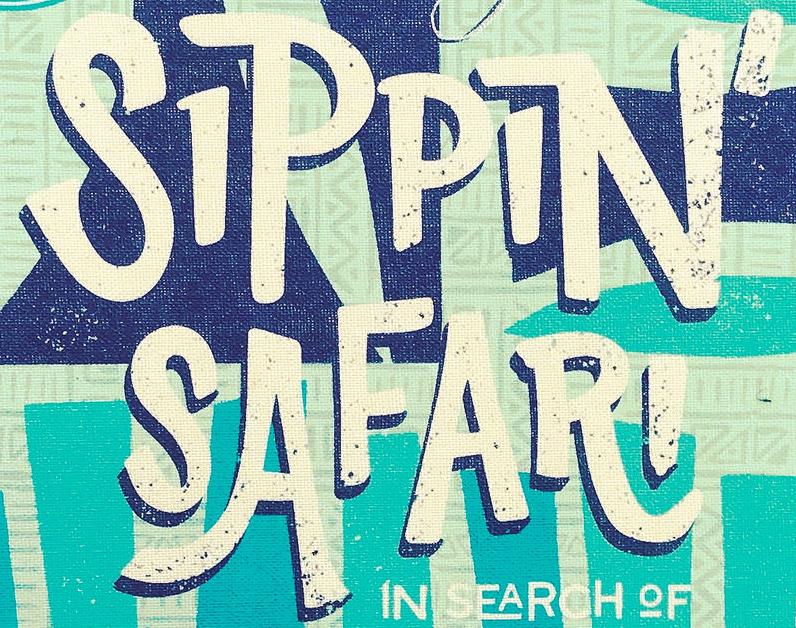
Suche Schriften dieses Buchcovers (Beachbum Berry's Sippin' Safari)
So unterschiedlich, wie gleiche Buchstaben hier in „Sippin’ Safari“ ausgeformt wurden (man vergleiche S, A, P und I), denke ich, dass der Schriftzug nicht aus einer Satzschrift gesetzt, sondern handgezeichnet wurde.
Die Originalausgabe des Buches (2007) wurde von SLG Publishing gestaltet. Deren im Impressum angegebene Domain www.slgcomic.com gibt es nicht mehr, die (kleine) Firma scheint aber noch zu existieren, du  findest sie unter https://store2.artboutikidtg.com/. Vielleicht haben Sie ja auch das Cover der 2017er  Jubiläumsausgabe gemacht, aus dem dein Ausschnitt stammt. Oder einfach Jeff Berry über seine von dir oben verlinkte Seite kontaktieren.
Sonderlich "Tiki-mäßig" finde ich die beiden Schriften übrigens nicht. Da findest du im Innenteil des Buches imho wesentlich bessere und typischere Beispiele, z.B. die Kapitelüberschriften und natürlich die Schriften auf den unzähligen Originalabbildungen aus der Tiki-Ära (vgl. nur das Schild am Beachcomber's in Palm Springs, S. 66). Auch eine Google-Bildersuche nach "tiki fonts" liefert jede Menge Passendes.
Sieht ganz so aus, auch beim Autorennamen darunter ist kein Buchstabe wie der andere und soweit ich sehe, kommt die Schrift auch sonst nirgends im Buch vor.
Was allerdings auch bei einer Satzschrift nicht verwunderlich wäre, kommt doch jeder der Buchstaben nur jeweils einmal vor.
Haha ... Ich meinte natürlich nur die vielen doppelt oder dreifach vorkommenden Buchstaben in SIPPIN SAFARI BY JEFF BERRY.